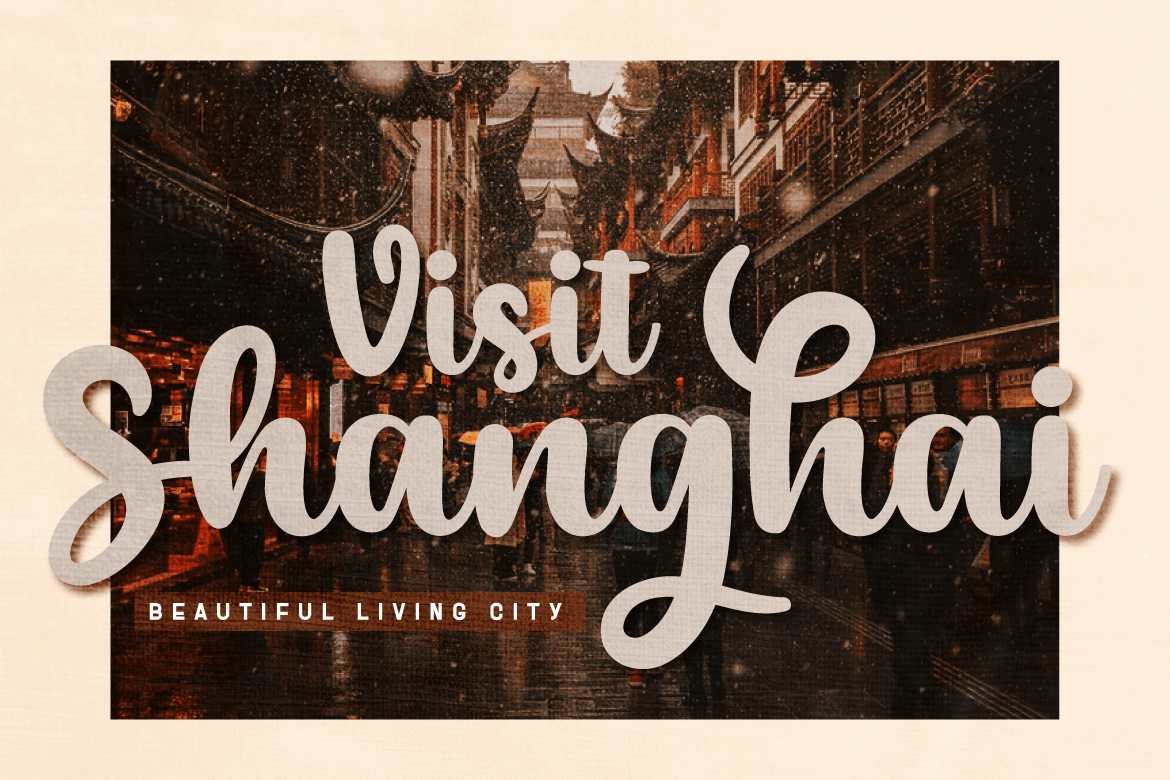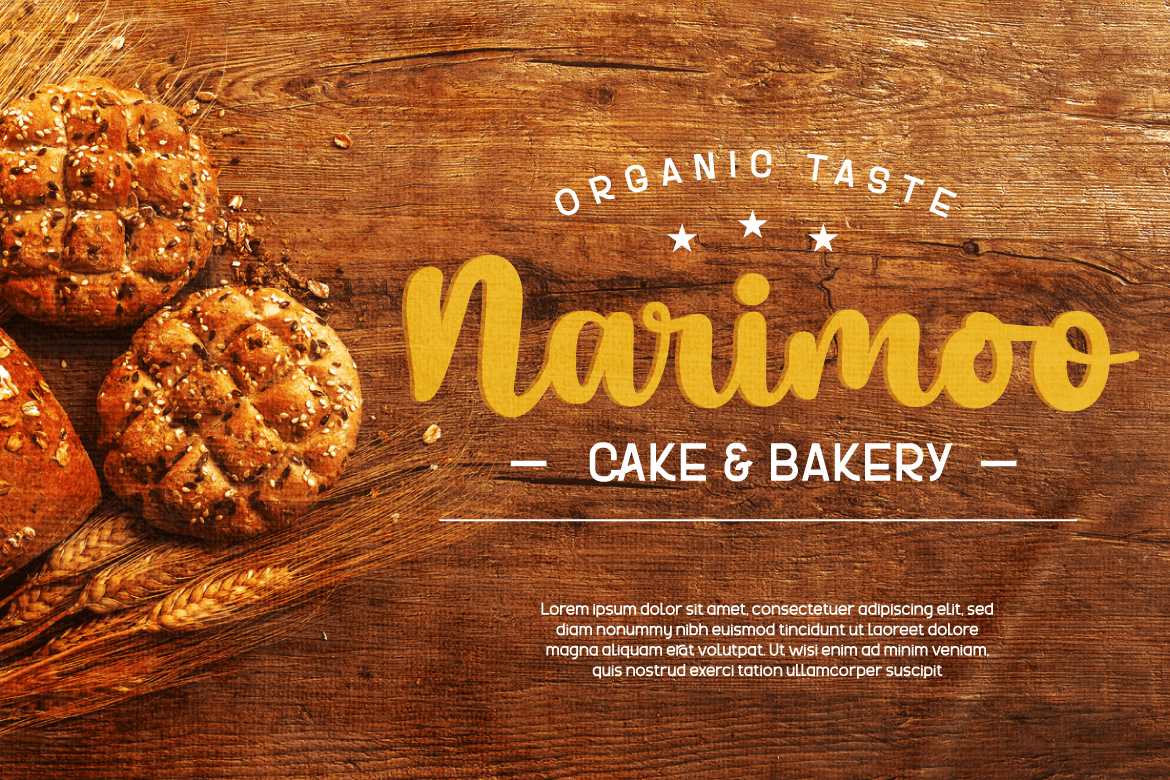
羞怯是一种手工书写的粗体字体,有着各种独特风格的背景和真实背景。字体有着各种各样的参考,可以给人留下深刻的印象,因此当你在项目中使用它时,信息将被有力地传递给听众。这种字体是根据你的需要设计的,也带有锐利和触感,具有可选功能、连字和多语言支持,因此此字体适用于工艺品、户外活动、标识、海报、标题、横幅、婚礼宣传、产品包装标识、报价、社交媒体封面、,书皮和更多。羞怯是一种手工书写的粗体文字字体,有着各种各样的经典风格和真实的背景。字体有着各种各样的参考,可以给人留下深刻的印象,所以当你在项目中使用它时,信息将被有力地传达给听众。这种字体是根据你的需要设计的,以便于阅读,同样采用Anatural和Touch设计,具有可选功能、连字和多语言支持,因此该字体适用于工艺品、户外活动、标识、海报、标题、横幅、婚礼宣传、产品包装标识、报价、社交媒体封面、书皮等。